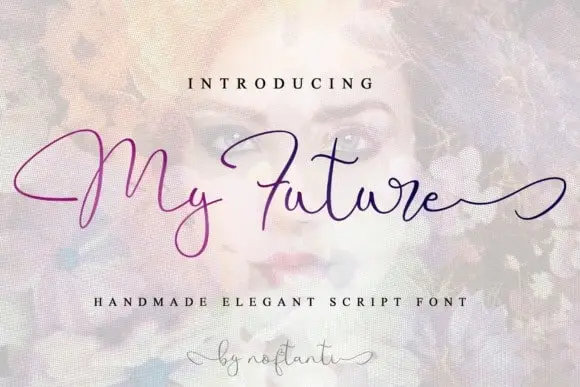
My Future Script Font – Download Grátis
A My Future Script Font é uma escolha perfeita para quem busca adicionar um toque sofisticado e moderno a projetos design. Ela surge como uma mistura única entre chamada elegante e escrita manual casual, criando um visual atemporal e único que se encaixa perfeitamente em qualquer projeto de design. Este tipo de fonte foi desenvolvido pelo designer noftanti na 99designs e traz sua própria cara ao trabalho, tornando-a uma excelente opção para aqueles buscando uma alternativa criativa às fontes tradicionais. Com seu estilo fresco e moderno, a My Future Script Font é ideal para gráficos de marca, design editorial ou qualquer projeto que busque dar um destaque especial à tipografia.